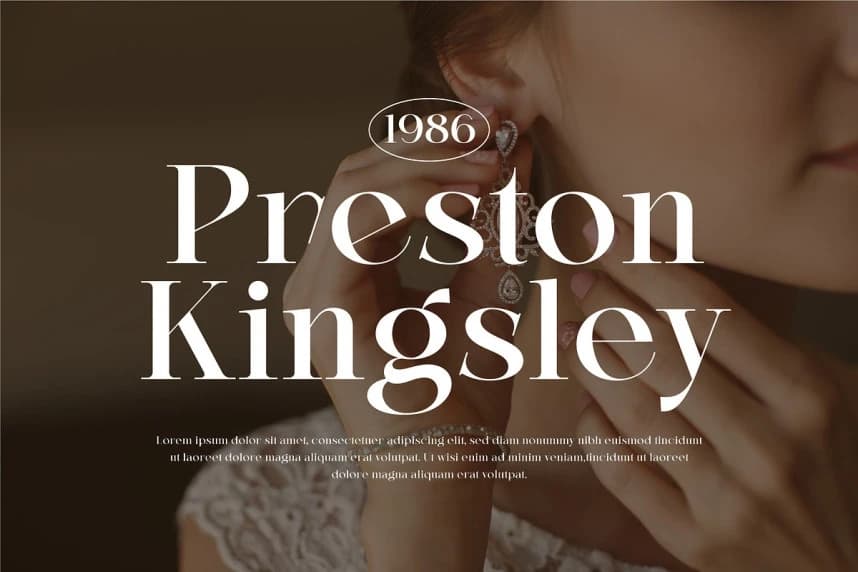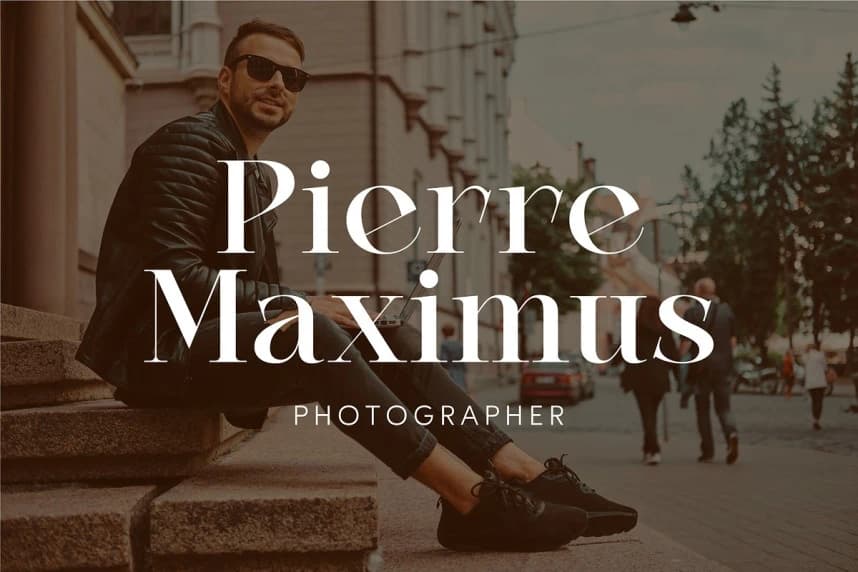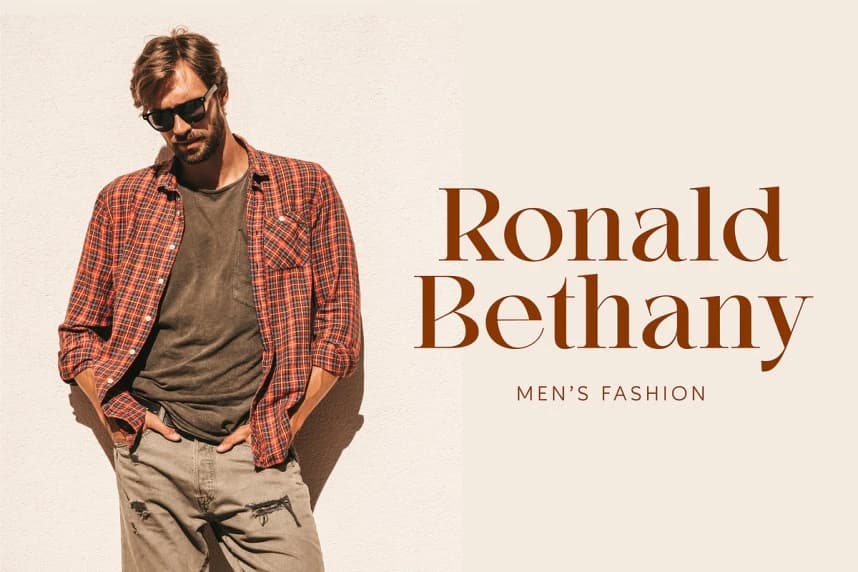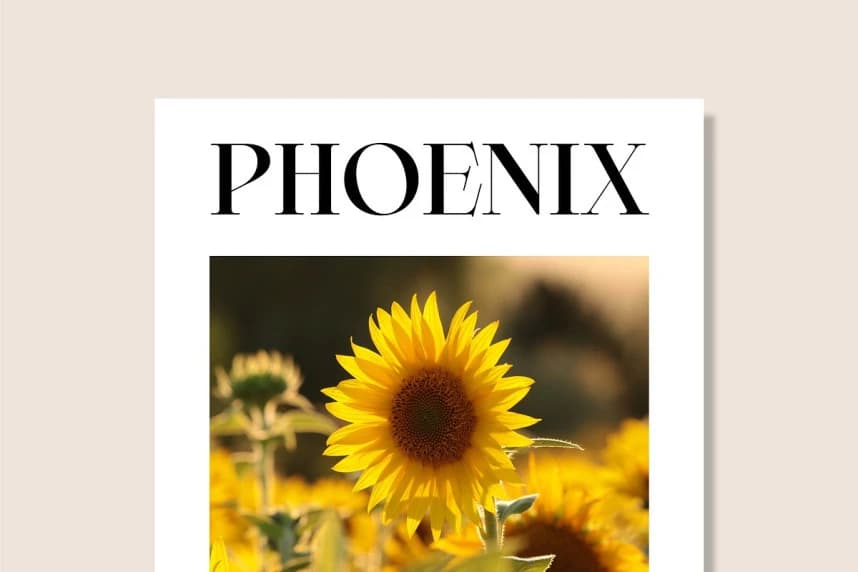
Averie Brenton Font
Averie Brenton Font zarif bir serif yazı tipi ailesidir. Davetiyeler, etiketler, logolar, dergiler, kitaplar, tebrik ve düğün kartları, ambalaj, moda, makyaj, kırtasiye, romanlar ve herhangi bir reklam amacı için mükemmel biçimde uygulanabilir.
- Serif Yazı Tipi
Averie Brenton Font zarif bir serif yazı tipi ailesidir. Davetiyeler, etiketler, logolar, dergiler, kitaplar, tebrik/düğün kartları, ambalajlar, moda, makyaj, kırtasiye, romanlar ve herhangi bir reklam amacı için mükemmel bir uyum sağlar.